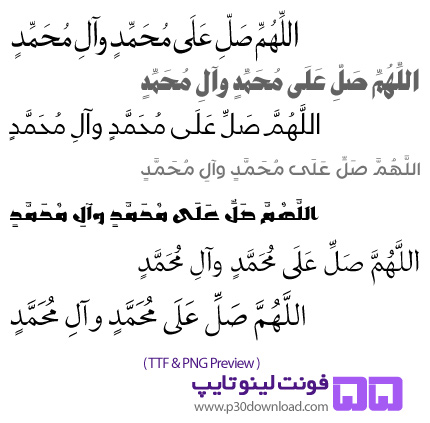
دانلود مجموعه فونت عربی، فارسی و اردو لاینوتایپ LinoType Arabic, Persin, Urdu Font
شما کاربران گرامی شاهد فونت عربی، فارسی و اردو لاینوتایپ با فرمت TTF هستید که میتوانید آن ها را درطراحی های گرافیکی خود به کار ببرید. طراحان و گرافیست های خلاق می توانند از این فونت زیبا در طراحی های خود استفاده کنند.
شرکت بزرگ لاینوتایپ که در سال ۱۸۸۶ ابتدا با نام همان دستگاه چاپ لاینوتایپ به جهان معرفی شد مسیر طولانی و پرپیچ و خمی را طی کرد تا امروزه به عنوان یکی از معتبرترین شرکتهای طراحی تایپ و فونت شناخته شود. از همان ابتدا که این شرکت وارد کشورهای عربی و ایران شد حرکتی جدی در طراحی و پیاده سازی تایپ فیسهای فارسی/عربی داشت.نکته دیگر اینکه شرکت لاینوتایپ فونتهایش را با پسوند LT (و نه پیشوند!) منتشر میکند. اصلی ترین فونت های این بسته به ترتیب فونت نازنین، فونت بدر، فونت جلال، فونت کریم، فونت لوتوس، فونت میترا و فونت یاقوت هستند که در در ایران و زبان فارسی بسیار پرکاربردتر هستند وجه تمایز این فونتهای با نسخه سری بی (BoranRayaneh Fonts) این است که در ویرایش اختصاصی شرکت لاینوتایپ این فونتها از حروف عربی، فارسی، اردو پشتیبانی میکند و در عین حال حروفی مشابه و هم اندازه لاتین را در خود دارد.